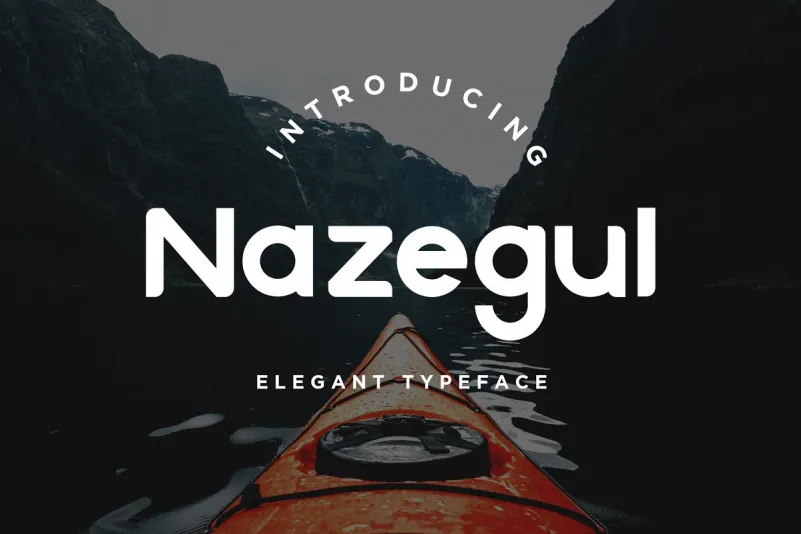
A Nazegul Typeface é uma moderna tipografia sans serif criada pela Guna Studio. Esta família de fontes é extremamente versátil e pode ser aplicada tanto em designs vintage quanto contemporâneos, oferecendo um leque vasto de possibilidades. Introduzindo a Nazegul Font, você tem à sua disposição uma solução perfeita para diversos projetos, como logotipos e identidades, convites, outdoors, folhetos de aniversário, embalagens de produtos, marcas de produto, design fotográfico, marcações digitais, posts nas redes sociais, publicidade, além de aplicações específicas como eventos especiais ou até mesmo cartazes para filmes. Com a sua simplicidade elegante e moderna, a Nazegul Font não apenas oferece uma aparência minimalista e futurista, mas também se adapta facilmente aos estilos mais diversos do design. Este é um recurso gráfico indispensável que certamente terá seu lugar em qualquer projeto de design visual. Não importa o tamanho ou natureza do trabalho, a Nazegul Font está aqui para ajudar você a dar vida à sua arte e ideias de uma maneira clara e moderna.